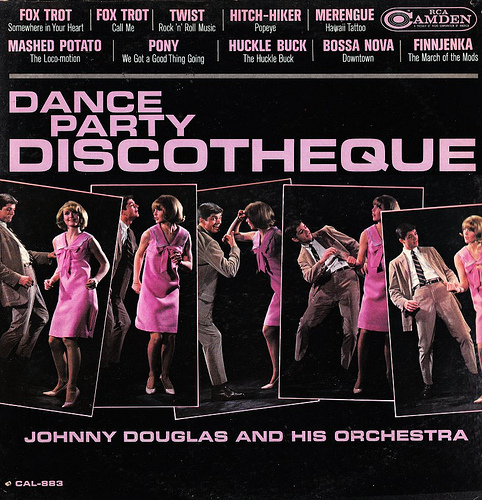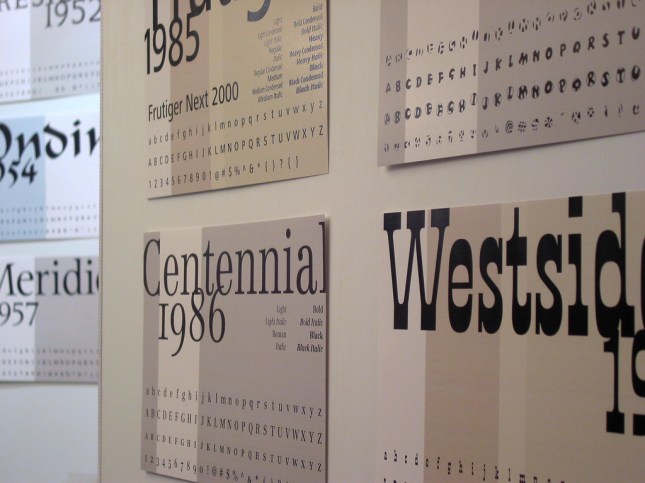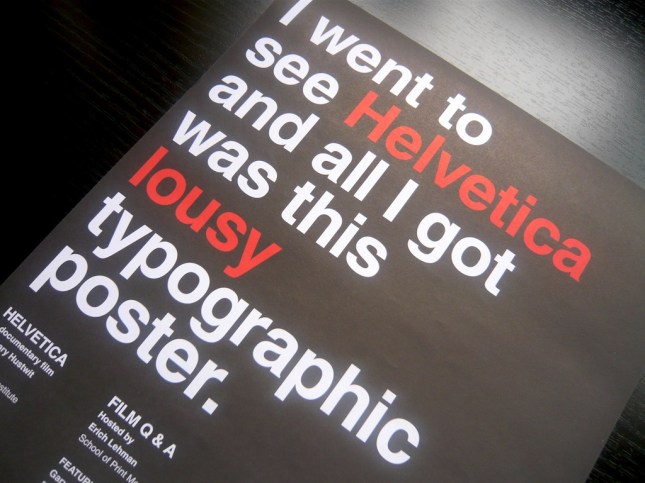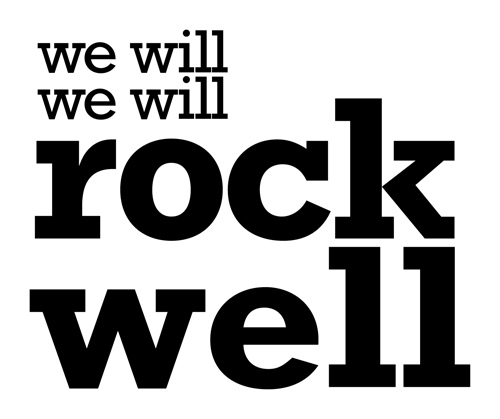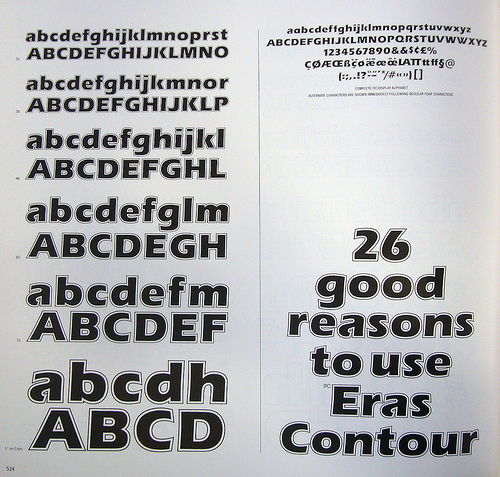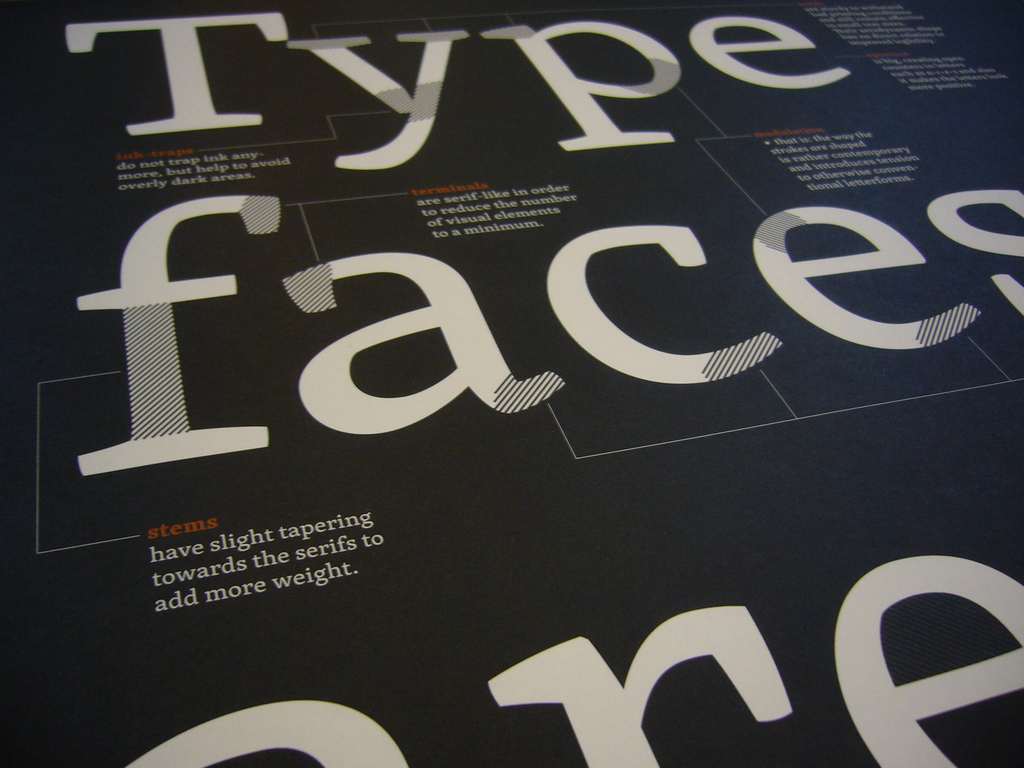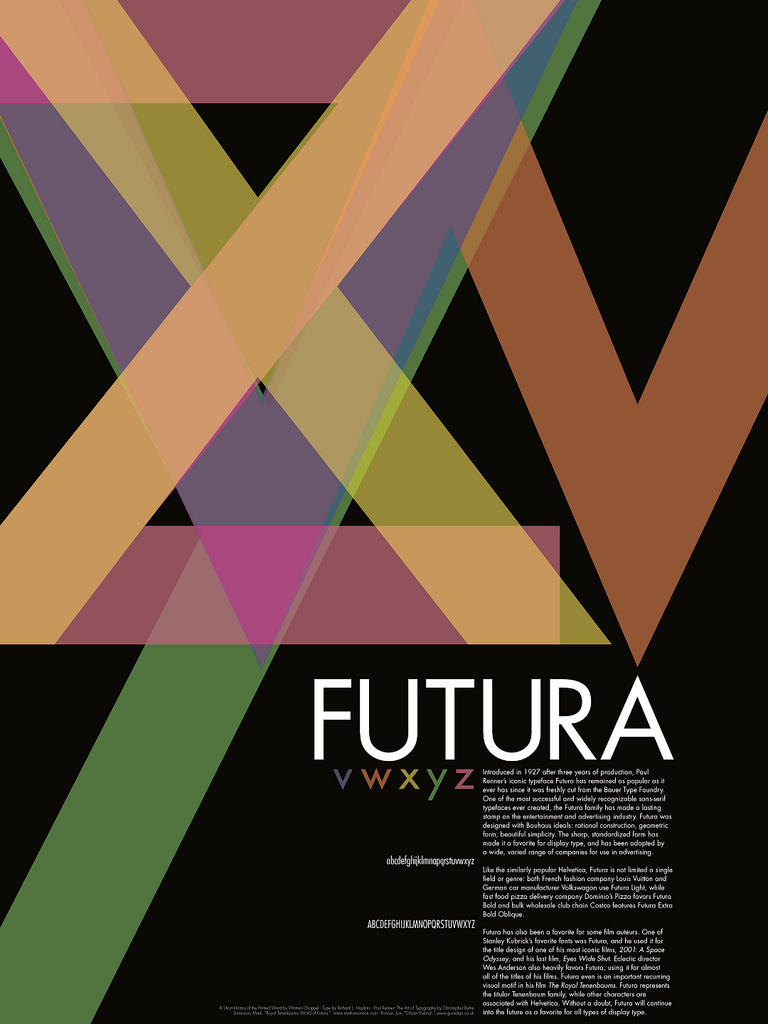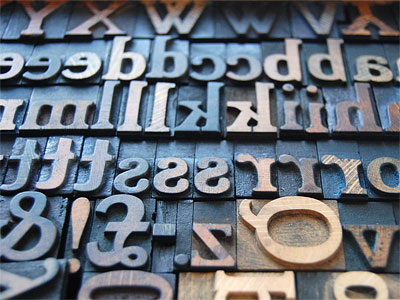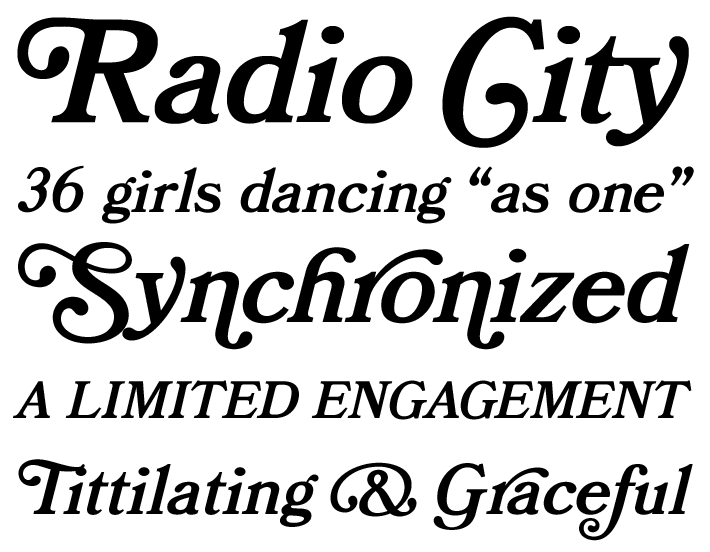
Trece maneras de ver a una Tipografía
En mis primeros diez años de mi carrera, trabajé para Massimo Vignelli, un diseñador que es legendario por usar un número muy limitado de tipografías. Entre 1980 y 1990, la mayoría de mis proyectos fueron acomodados en cinco fuentes: Helvetica (naturalmente), Futura, Garamond No.3, Century Expanded, y, por supuesto, Bodoni.
Para Massimo, estas eran las elecciones ideales y con una ética imperativa. “En la nueva era de la computadora,” él escribió alguna vez, “la proliferación de tipografías y la manipulación de los tipos representan un nuevo nivel de contaminación visual que amenaza a nuestra cultura. De cientos de tipografías, todas lo que necesitamos son unas cuantas básicas y el resto son basura”. Para mí, se convirtió en un sistema ahorrador de tiempo. ¿Para qué pasar horas escogiendo entre Bembo, Sabon y Garamond No.2 cada vez que necesitas una Romana Veneciana? Para la mayoría de la gente – mi mamá por ejemplo – estas eran distinciones sin diferencias. ¿Porqué no solamente comprometerse con la Garamond No.3 y nunca volver a dudar? Mi educación de escuela católica debió haberme preparado muy bien para este tipo de claridades morales. Lo acepté agradecido.
Entonces, después de una década, dejé mi primer trabajo. De pronto pude usar cualquier tipografía que quise, y me volví loco. En uno de mis primeros proyectos, usé 37 fuentes diferentes en 16 páginas. Mi esposa, que había asistido a una escuela católica, encontró todo esto muy familiar. Recordó a sus compañeras que se habían cambiado a escuelas públicas después de ocho años bajo las monjas. Liberados al fin del recato de los uniformes, ellos usaron las faldas más cortas que pudieron encontrar. “Jesús”, dijo ella, viendo a uno de mis múltiples derbies de demolición tipográfica. “Te has convertido en una verdadera zorra, ¿no?”
Era cierto. Liberado de la monogamia, me hice tipográficamente promiscuo. Desde entonces, creo, he aprendido a manejar mi comportamiendo – como cualquiera que abusa una sustancia, aprendí que los atracones son consumidores de tiempo, costosos y por último, contraproducentes – pero nunca he vuelto a cinco – sobriedad tipográfica. Esos cientos de fuentes siguen ahí afuera, pero mi recuperación ha requerido que me vuelva más discriminante y salga con respuestas a esta aparentemente simple pregunta: ¿porqué elegir una tipografía en particular? He aquí trece razones.
1. Porque funciona.
Algunas tipografías son simplemente perfectas para ciertas cosas. He especificado fuentes exóticas en programas de identidad que funcionan bellísimamente en títulos y hasta en textos, pero tarde o temprano debes colocar esa tipografía pequeñita en el fondo de la tarjeta de presentación. Esto es para lo que sirve la Franklin Gothic. Cuidado, piensa: algunas tipografías funcionan demasiado bien. Frutiger ha sido usada tanto para los sistemas señaléticos en hospitales y aeropuertos que cuando la veo me hace sentir que estoy a punto de ser diagnosticado con un tumor cerebral o que perdí el vuelo de las 7:00.
2. Porque te gusta su historia.
He escuchado de varios proyectos deonde los diseñadores encontrar una fuente que fue creada el mismo año que la empresa del cliente fue fundada. Esto debe darle la recomendación de un aura de destino manifiesto que sea positivamente irresistible. Todavía no he tenido esa suerte todavía. Pero sigo buscando el mismo tipo de evocación. Por ejemplo, nunca fui fan de la Eurostyle de Aldo Novarese, pero llegué a amarla mientras trabajaba en un monograma para Eero Saarinen: Ambos compartían esa expresividad peculiar del optimismo de posguerra de los años 50.
3. Porque te gusta su nombre
Alguna vez vi un proyecto en el portafolio de un estudiante que subestimó el dudoso desafío de rediseñar la identidad de Tiffany’s. Particularmente me disgustó la tipografía que fue usada, y amablemente le pregunté qué era. “oh”, fue su respuesta entusiasta, “¡esa es la mejor parte! ¡se llama Tiffany!». Por otra parte , Bruce Mau diseñó Spectacle, el libro que creó con David Rockwell, usando la tipografía Rockwell. Creí que esto era gracioso.
4. Por quién la diseñó.
Alguna vez trabajaba en un proyecto donde el grupo del cliente incluía algunos arquitectos de mentalidad recalcitrante. Elegí Cheltenham, una tipografía idiosincrática que no solamente era adecuado a los requerimientos del proyecto, pero era una de las pocas que conozco que fue diseñada por un arquitecto, Bertram Goodhue. Recientemente, diseñé un programa de publicaciones para una escuela de niñas. Usé una tipografía que fue diseñada por una mujer y nombrada por otra, Mrs. Eaves de Zuzana Licko. En ambos casos, mis clientes supieron que público siempre iba a pasar desadvertida la historia detrás de la selección de la fuente, y sin embargo tuvieron algo de confort. Yo también.
5. Porque estaba ahí.
A veces, una tipografía se mantiene viva con la premisa de que aparecerás, y parece estar dispuesta a evitarlo. “Solemos usar Baskerville y Univers 65 en todos nuestros materials, pero nos sentimos libres de hacer una sugerencia alterna” “¿en verdad? ¿Por qué molestarnos? Es como uno de esos shows donde le dan a un chef amateur un nabo, un costal de harina, una pierna de carnero y algo de miel de maple y le dicen que debe hacer un platillo de eso. A veces, es algo que nuca has usado, pero lo hace aún más divertido.
6. Porque te obligan.
Y, a veces es algo que nunca has usado antes, por alguna razón te dicen “usamos ITC Eras en todos nuestros materiales.” “¿puedo hacer una sugerencia alterna?” “No.” Aquí es cuando los machotes se vuelven útiles.
7. Porque te recuerda algo.
Cada vez que quería hacer que las palabras lucieran francas, convencionales e inteligentes, consideraba a Futura, en caja alta y baja. ¿Por qué? No porque Paul Renner fuera franco, convencional e inteligente, algo que además ha de haber sido. No, es porque hace 45 años Helmut Krone decidió usar Futura en la publicidad para Volkswagen de Doyle Dane Bernbach, y se sigue usando hoy en día. Una advertencia, como sea: lo que a ti  te recuerda algo puede recordarle algo más a otra persona.
¡Dios, es que son de las mejores! Casi coincido con ese diseñador, poco más hace falta :). Tal vez Century Gothic… Aunque ya está la Futura, que es sencillamente sensacional.